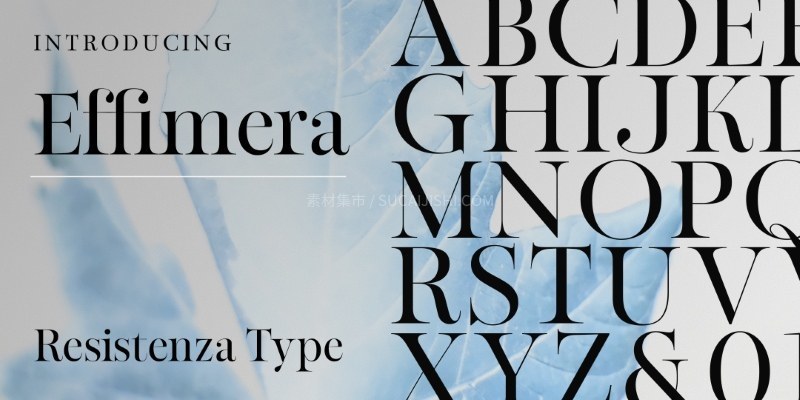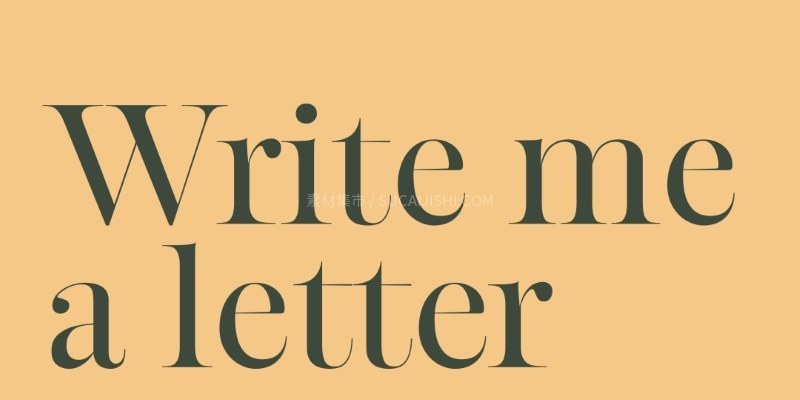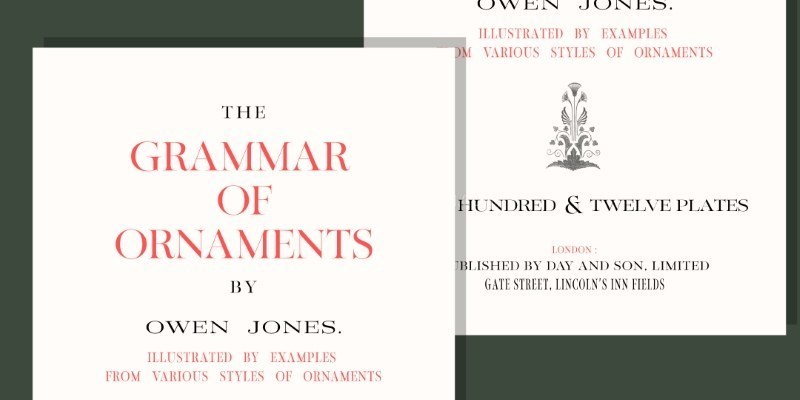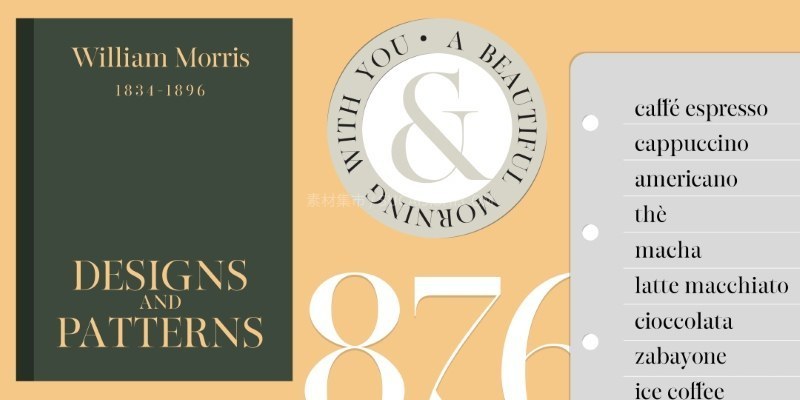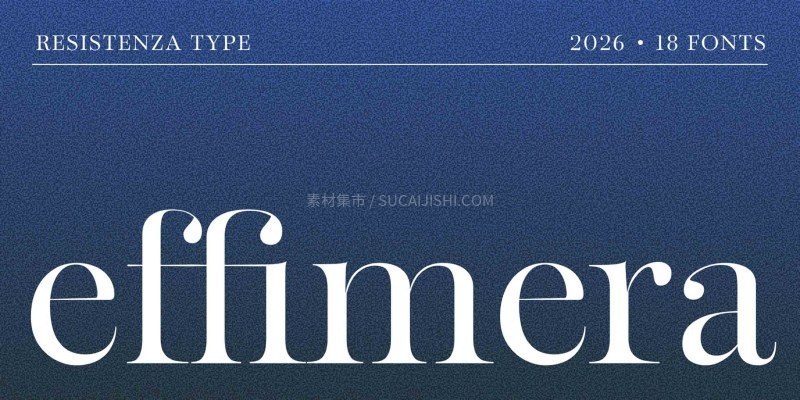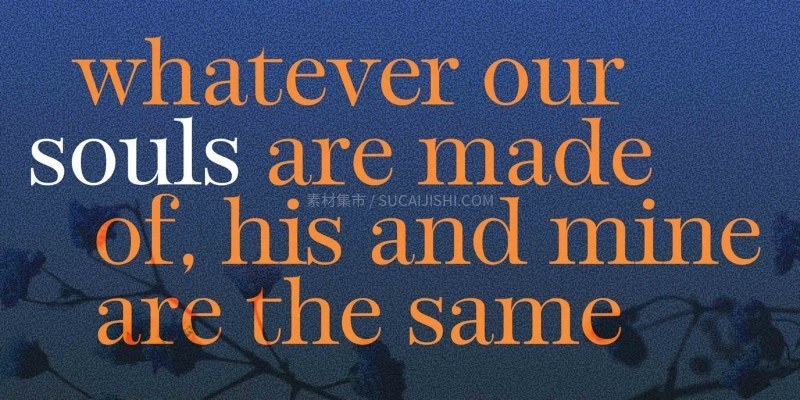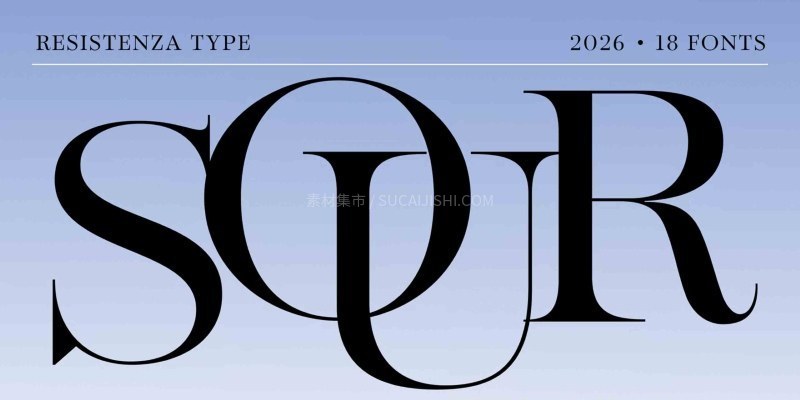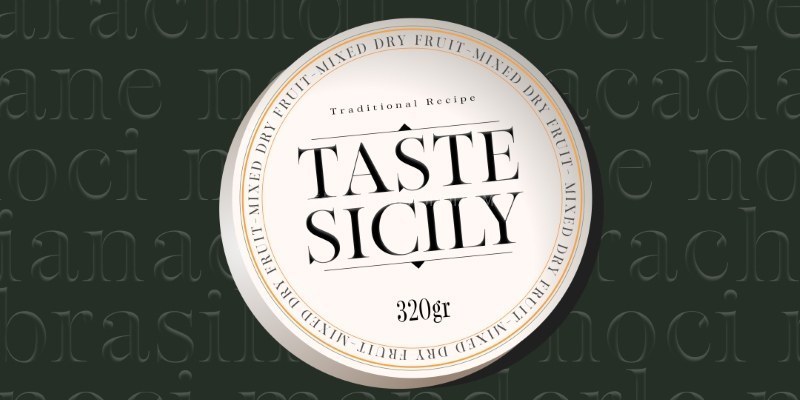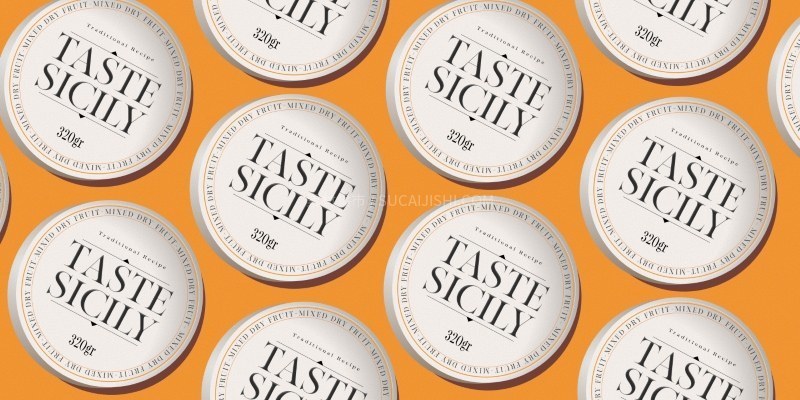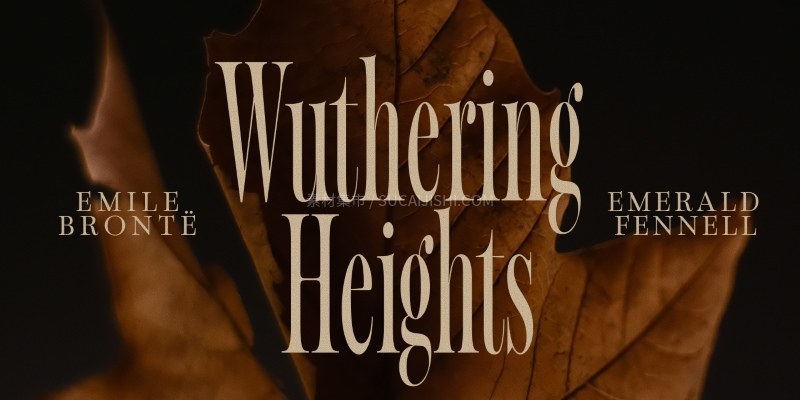
Effimera高对比度现代衬线可变字体家族
Effimera 是一款高对比度的现代衬线字体,散发着优雅、精致和奢华的气息。它属于 Didone 字体系列,设计精巧,垂直笔画粗细对比鲜明,衬线清晰锐利。字母“g”和“a”的球形笔画末端等独特细节,增添了一丝精致的装饰性,更显其优雅气质。大写字母采用修长的垂直比例,而较大的 x 高度则确保了在大字号下的清晰易读。Effimera 的灵感源自 Bodoni 和 Didot 等经典字体,是对永恒风格的现代诠释。这款字体在高端视觉环境中表现出色,尤其适合风格与精致至关重要的场合。它特别适用于奢侈品牌、时尚杂志、化妆品包装、杂志标题和高端活动宣传。无论用于印刷还是数字格式,Effimera 都能带来一种沉稳优雅的气质,使其成为追求美感和精致感的设计环境的理想之选。
这套字体的数字设计极其有特色,做体育赛事计时或者大屏数据的可视化大屏,极其抢眼。